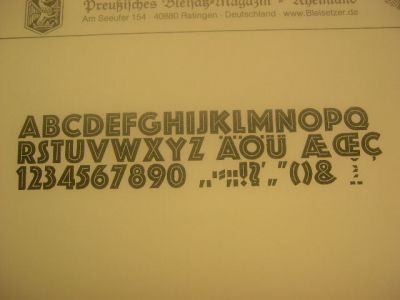
Fraktur – aber wo?
>Ja, das ist eine Schrift von Jakob Erbar von 1924, Schriftgießerei Ludwig & Mayer.
Super, diese Begleitinfos würde man (ich) sonst nie erfahren.
>Die Lichte Fette Grotesk gefällt mir hervorragend. Die empfinde ich sogar tatsächlich als "preußisch" - nicht im korrekten historischen Sinn, aber als Adjektiv
Hmmm, was hat die Lichte Fette Grotesk mit "preußisch" zu tun - verstehe nur Bahnhof. Kläre mich mal auf, was du unter diesem "mythischen Preußen" verstehst, hinsichtlich Schriften und deren Gestaltung. Ich denke das würde uns ein paar "politische" Diskussionen ersparen...
die Lichte Fette Grotesk ist in der Mitte ausgespart, interessant... gibt es diese auch schon im Andruck?
ja, hier ein Foto von einem Andruck.
Preußisch in Bezug auf eine Schrift empfinde ich (rein subjektiv) die klaren Linien ohne Schnörkel und Spielereien. Die Schrift hat eine starke Ausstrahlung und hohen Wiedererkennungswert. Sie stammt aus dem Jahr 1924. Das war eine Zeit, in der sich Deutschland nach den Wirren der Revolution gerade wieder ein bißchen beruhigt hatte. Aus damaliger Sicht war diese Schrift sehr mutig (meine ich). Müßte ich sie charakterisieren, würde ich sagen: Offen, ehrlich, gerade heraus mit einer glasklaren Aussage. Und das, entschuldigung, sind für mich preußische Eigenschaften.
Häng Dich nicht an meiner Bezeichnung auf.
Ich habe ein so völlig anderes Weltbild und andere Wertvorstellungen, daß Du sie kaum wirst verstehen können. Das ist auch nicht nötig. Ich will Dir meine gar nicht aufdrängen.
Das Foto ist leider miserabel.
schönes bild bleisetzer, da kommen erinnerungen hoch.
ich habe damals in dieser schrift meinen ersten briefbogen gesetzt ...
Bleisatz macht süchtig. Es gibt jede Menge Typographen, die ab und an wieder Blei in die Hände bekommen wollen. Mir ging's vor ein paar Jahren genau so.
Offen, ehrlich, gerade heraus mit einer glasklaren Aussage. Und das, entschuldigung, sind für mich preußische Eigenschaften.
Auch wenn das jetzt ins Off-Topic abschlittert und vielleicht sogar in Streit endet:
Sind das nicht positive Eigenschaften, die man sich einfach selbst gerne andichtet? Ich glaube kaum dass sich ein Franzose, Türke oder Bayer selbst als verschlossen, verschlagen oder kompliziert bezeichnen würde.
Ich als Alemanne (eigentlich bin ich Europäer, aber damit ist schlecht Gegenposition zu beziehen) und somit Nicht-Preusse und Außenstehender habe eher den Eindruck preussische Eigenschaften seien verklemmt, starr, überstrukturiert und kalt. Wer hat nun recht?
Ich habe ein so völlig anderes Weltbild und andere Wertvorstellungen, daß Du sie kaum wirst verstehen können. Das ist auch nicht nötig. Ich will Dir meine gar nicht aufdrängen.
Mit Verlaub, das tust du aber, indem du praktisch in jedem Beitrag Bezug auf Preußen nimmst, obwohl es hier eigentlich um Schriftgestaltung und Typografie geht.
Typographische Eigenschaften lauten anders, und selbst wenn sie da in manchen Fällen heißen "klar, gerade, geordnet, sauber" und das vielleicht mit den von dir dem Preussischen zugeordneten Eigenschaften kongruent ist, zweifle ich daran, dass eine Schrift dann deswegen "klar preußisch" ist, und dass das in praktisch jedem Beitrag herausgekehrt werden muss.
Geht es dir eigentlich primär um Preussen, oder primär um Schrift? Langsam habe ich Zweifel dass es letzteres ist.
Offen, ehrlich, gerade heraus mit einer glasklaren Aussage. Und das, entschuldigung, sind für mich preußische Eigenschaften.
Auch wenn das jetzt ins Off-Topic abschlittert und vielleicht sogar in Streit endet:
Sind das nicht positive Eigenschaften, die man sich einfach selbst gerne andichtet? Ich glaube kaum dass sich ein Franzose, Türke oder Bayer selbst als verschlossen, verschlagen oder kompliziert bezeichnen würde.
Ich als Alemanne (eigentlich bin ich Europäer, aber damit ist schlecht Gegenposition zu beziehen) und somit Nicht-Preusse und Außenstehender habe eher den Eindruck preussische Eigenschaften seien verklemmt, starr, überstrukturiert und kalt. Wer hat nun recht?
Nein, es gibt ganz sicher keinen Streit.
Ich hatte geantwortet auf den Frage:
"Hmmm, was hat die Lichte Fette Grotesk mit "preußisch" zu tun - verstehe nur Bahnhof. Kläre mich mal auf, was du unter diesem "mythischen Preußen" verstehst, hinsichtlich Schriften und deren Gestaltung. Ich denke das würde uns ein paar "politische" Diskussionen ersparen..."
Ich habe ein so völlig anderes Weltbild und andere Wertvorstellungen, daß Du sie kaum wirst verstehen können. Das ist auch nicht nötig. Ich will Dir meine gar nicht aufdrängen.
Mit Verlaub, das tust du aber, indem du praktisch in jedem Beitrag Bezug auf Preußen nimmst, obwohl es hier eigentlich um Schriftgestaltung und Typografie geht.
Auch das letzte Revival zum Thema "Blackletter Fonts" fing in den USA für ca. 20 Jahre an. Wo würden wir ohne die Totally Gothic und Sabbath Black (beide von Emigre) sein?
Das größte, beste Austellung, die es bisher über die Gebrochene Schriften gab, war 1998 in New York. Blackletter ist weltweit, und das ist schön so. Ich finde auch, das es kein geschlosses Thema es… es hat sich nur geändert. Alt heißt nicht immer besser.
Mehr über gebrochene Schriften werden in den nächsten zwei Ausgaben der Linotype Matrix höffentlich zu lesen. Mehr dazu, wenn die Hefte ins Handel kommen!